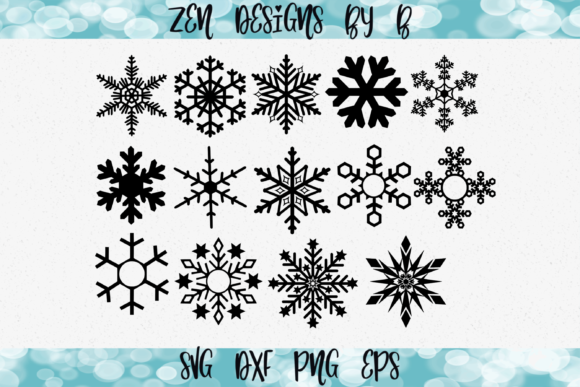
Snowflake Bundle
Jika anda sedang mencari aset berkualiti tinggi seperti Snowflake Bundle, pakej premium ini merupakan pilihan yang hebat untuk projek kreatif anda.
Dicipta dengan ketepatan, Snowflake Bundle menyediakan vektor yang bersih, tipografi yang licin dan lesen komersial untuk ketenangan fikiran.
Sama ada anda mencipta produk POD (Print on Demand), jemputan perkahwinan atau grafik media sosial, Snowflake Bundle amat bersesuaian.